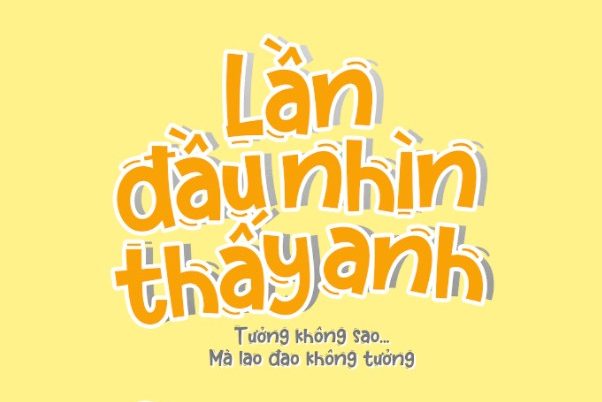
Font việt hóa MTD Summer Show
Giới thiệu về Font việt hóa MTD Summer Show
Nếu bạn đang tìm kiếm một bộ chữ mang phong cách phóng khoáng và tràn đầy năng lượng, Font việt hóa MTD Summer Show chính là lựa chọn hoàn hảo. Đây là mẫu Font Miễn Phí được cộng đồng designer yêu thích nhờ những đường nét mềm mại nhưng không kém phần phá cách. Bộ font này giúp các bạn học sinh và giáo viên dễ dàng tạo nên những bài thuyết trình ấn tượng hoặc các ấn phẩm truyền thông học đường đầy màu sắc. Phiên bản việt hóa chuẩn giúp loại bỏ hoàn toàn lỗi hiển thị dấu tiếng Việt, mang lại trải nghiệm thiết kế mượt mà nhất.
Ưu điểm nổi bật của Font việt hóa MTD Summer Show
Phong cách thiết kế hiện đại
Đặc trưng của Font việt hóa MTD Summer Show nằm ở sự kết hợp giữa nét vẽ tay thủ công và phong cách đồ họa hiện đại. Các ký tự được chăm chút tỉ mỉ, tạo cảm giác thân thiện và gần gũi. Điều này cực kỳ phù hợp cho các chủ đề về mùa hè, sự kiện dã ngoại hay các dự án sáng tạo của giới trẻ. Bạn có thể sử dụng font chữ này để làm nổi bật tiêu đề poster, thiệp mời hoặc các trang trí báo tường sinh động.
Khả năng ứng dụng linh hoạt
Không chỉ dùng cho tiêu đề, bộ font này còn hoạt động tốt trên các nền tảng mạng xã hội như Facebook hay Instagram. Nhờ cấu trúc rõ ràng, người xem có thể dễ dàng đọc được nội dung dù ở kích thước nhỏ. Đối với môi trường giáo dục, việc sử dụng các bộ font đã việt hóa giúp các em học sinh tiếp cận với tư duy thẩm mỹ mới mẻ, từ đó kích thích sự sáng tạo trong học tập và rèn luyện kỹ năng đồ họa cơ bản.